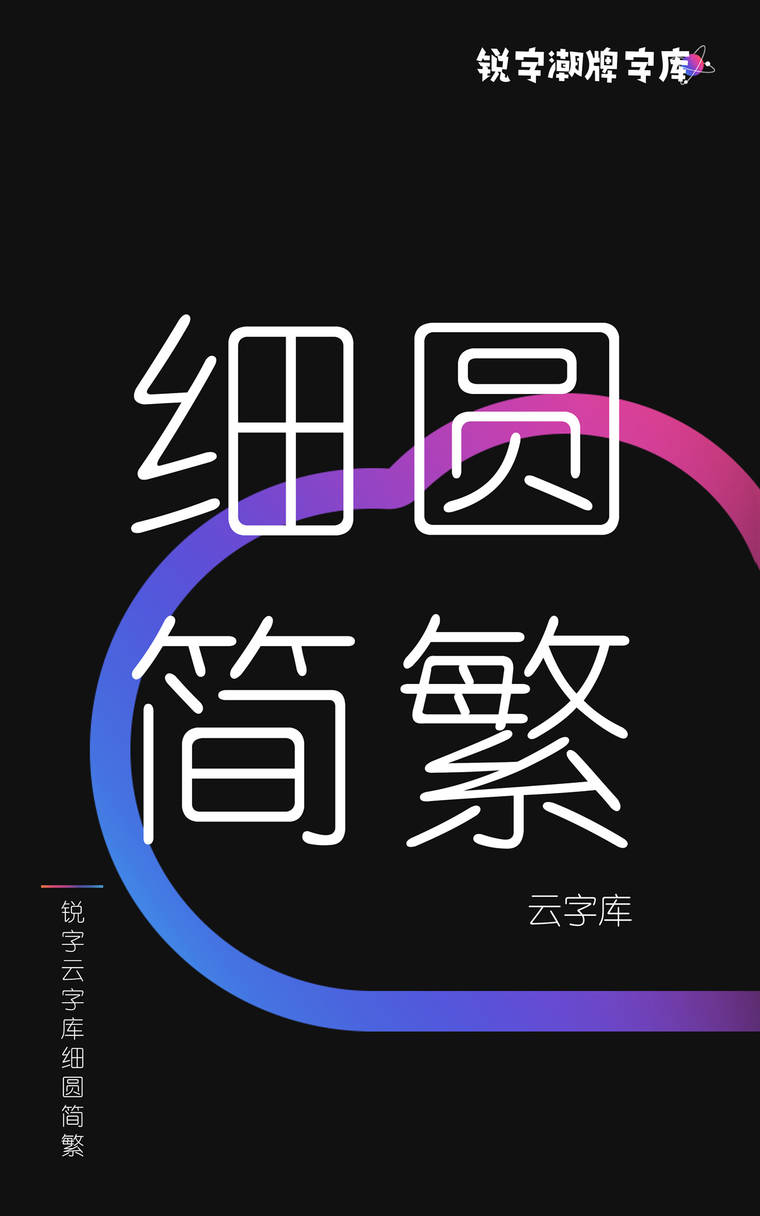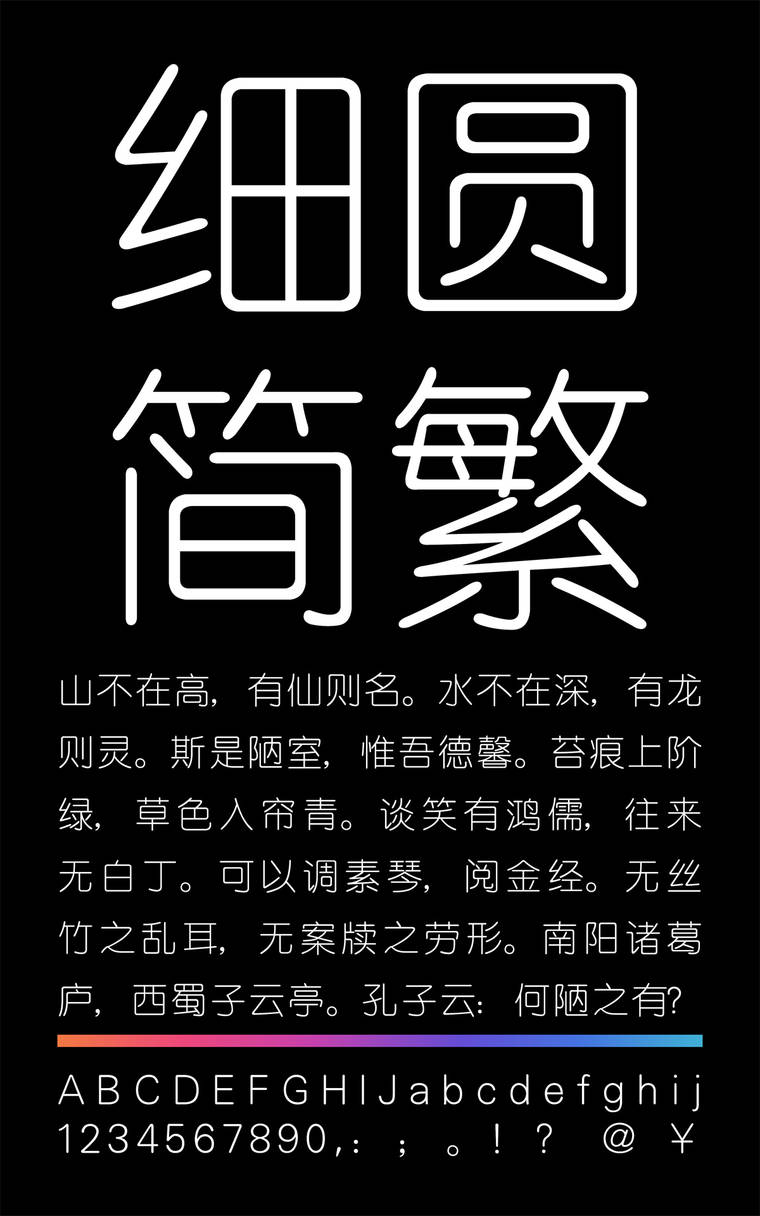
锐字云字库细圆简繁
锐字云字库细圆简繁,是云字库品牌字库旗下的一款字体。锐字潮牌字库拥有本字体独家版权,并提供锐字云字库细圆简繁的官方免费下载服务。
字体特征:粗细为较细,比黑体细,清瘦纤细,特点是没有衬线装饰,字面呈正方形,一笔一画都能清晰,撇捺等笔画不尖,字形端庄,笔画横平竖直,全部一样纤细,结构醒目严密。方正、朴素、简洁、无装饰、横竖笔形纤细视觉相等、笔形方头方尾、黑白均匀,因此非常醒目,运用广泛。